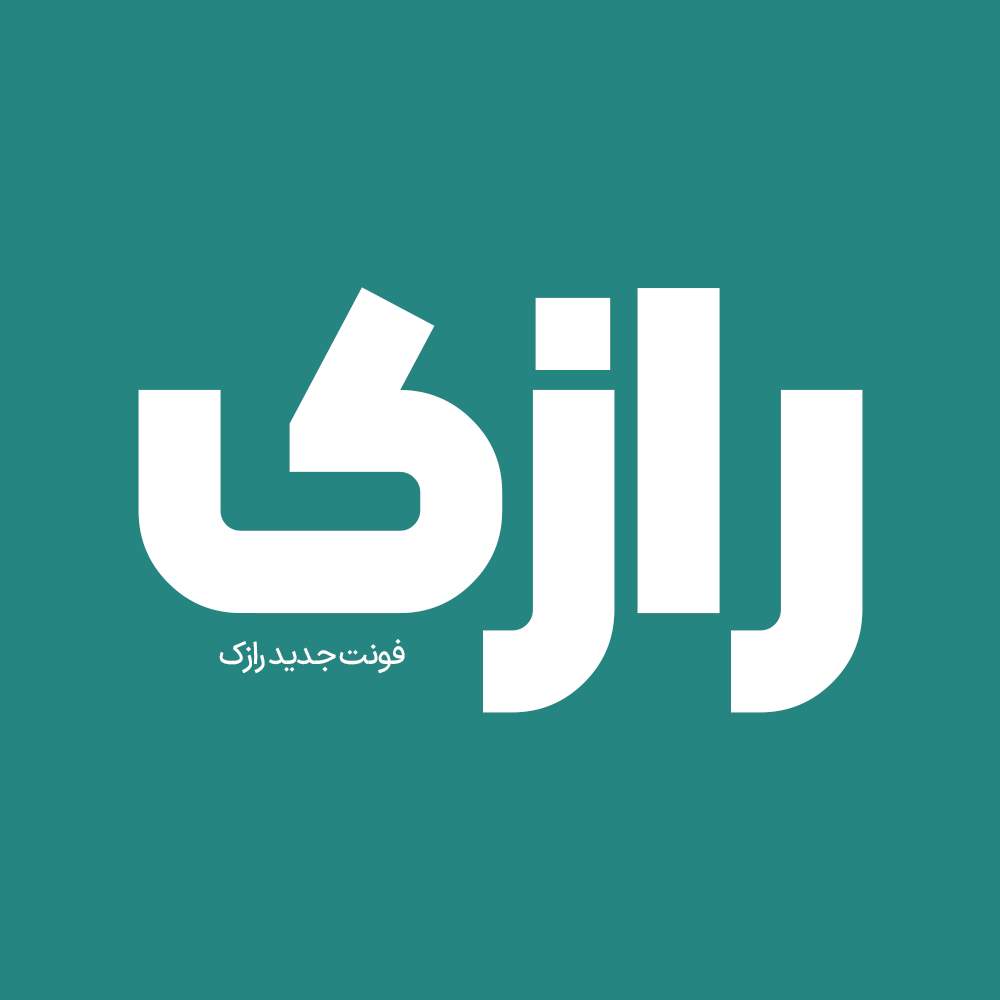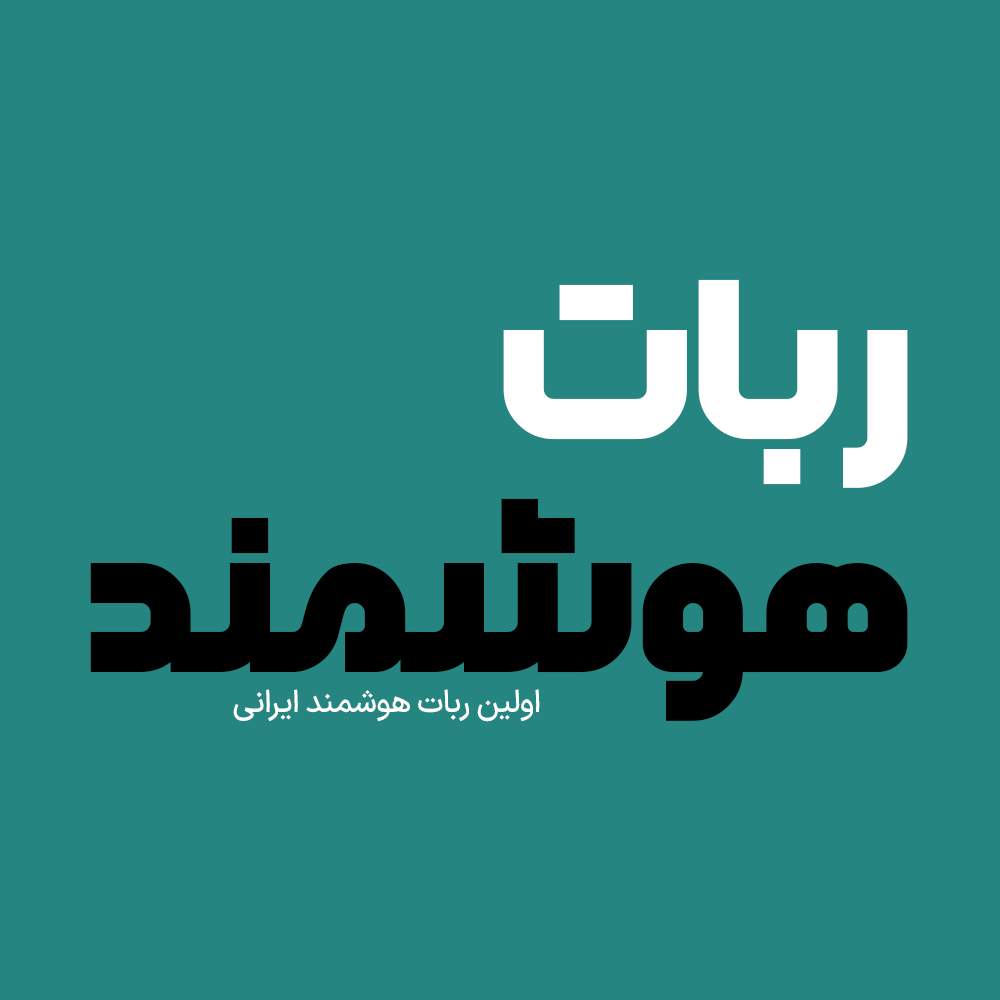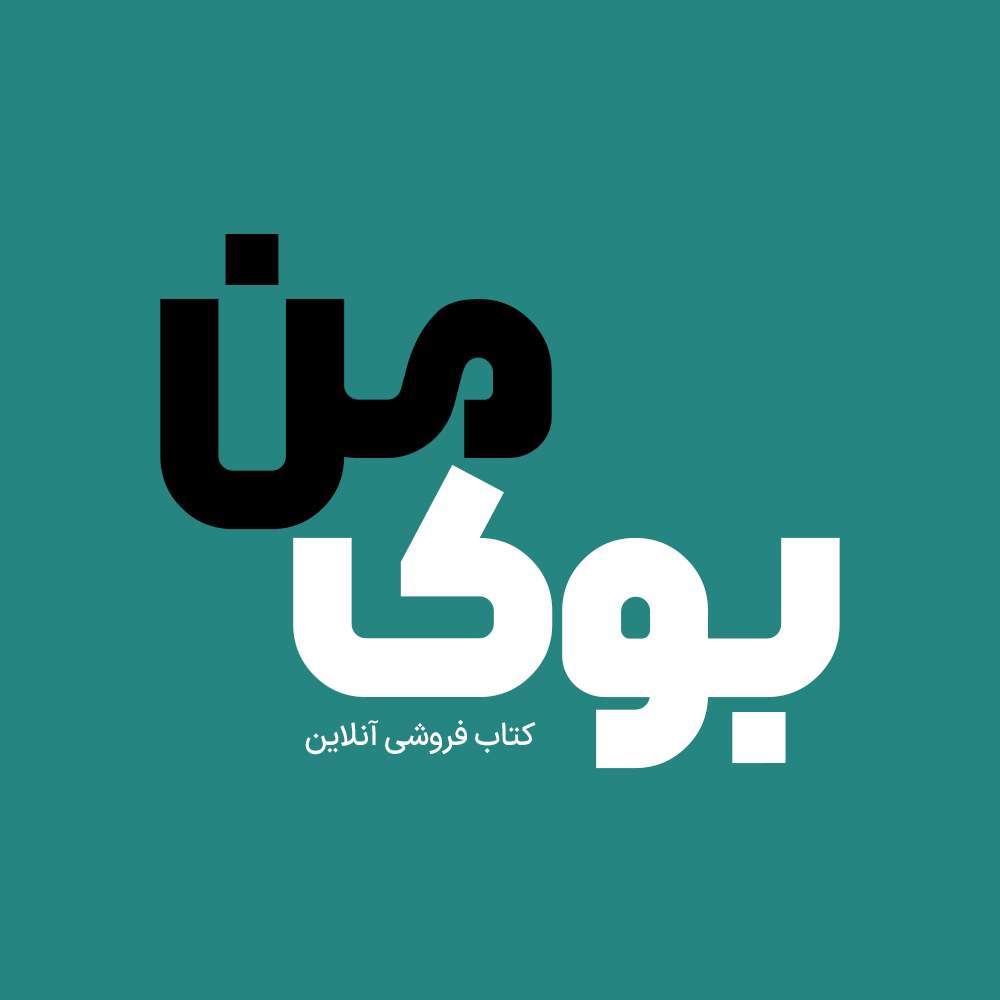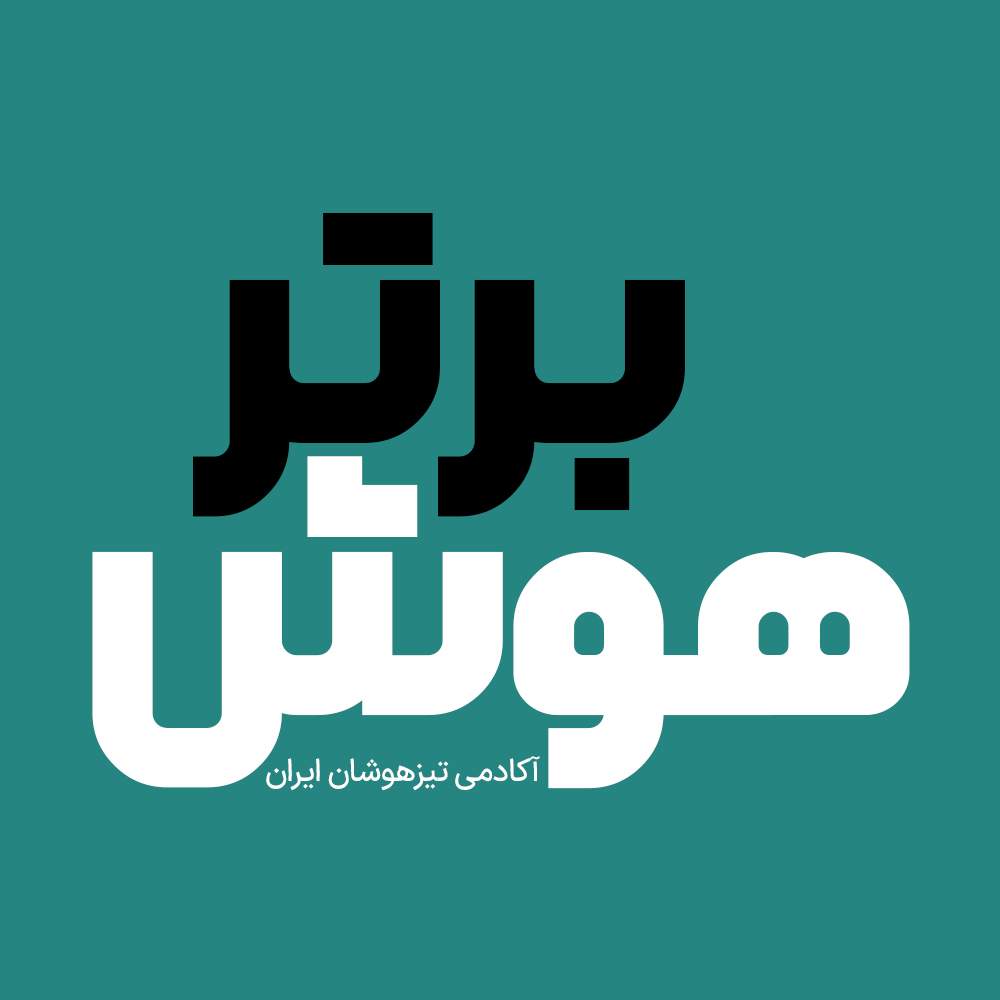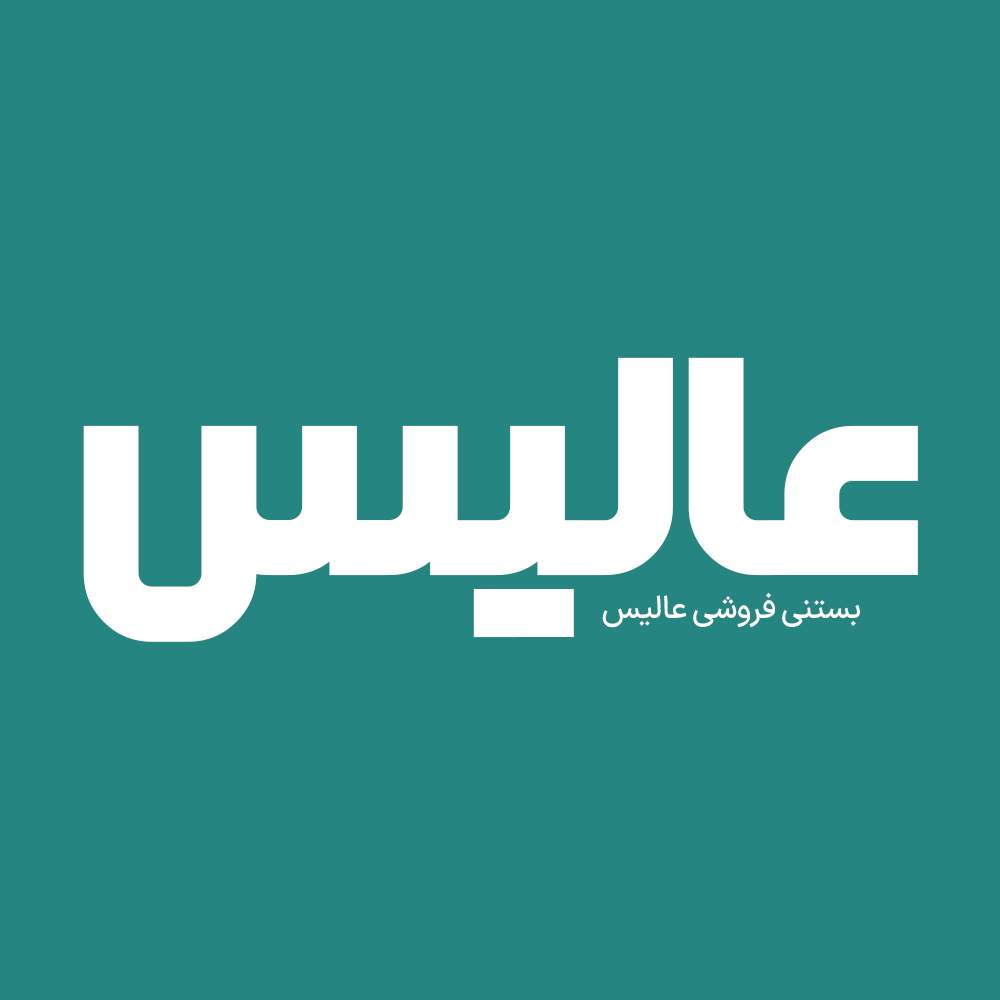
فونت فارسی رازک Razak Font
فونت فارسی رازک یک فونت زیبا و حرفه ای فارسی میباشد که مناسب طراحیهای خاص و متفاوت از جمله لوگوتایپ، تایپوگرافی و استفاده در پوسترهای تبلیغاتی…
فونت فارسی رازک یک فونت زیبا و حرفه ای فارسی میباشد که مناسب طراحیهای خاص و متفاوت از جمله لوگوتایپ، تایپوگرافی و استفاده در پوسترهای تبلیغاتی و… میباشد. همچنین از این فونت در طراحی تابلوهای چلنیوم هم به دلیل ساختار منحصر به فردش میتوانید استفاده کنید. در ادامه برای شما نمونه تایپهای این محصول حرفهای رو آماده کردیم که میتوانید مشاهده کنید.
پیشنمایش و نمونه تایپ های فونت رازک